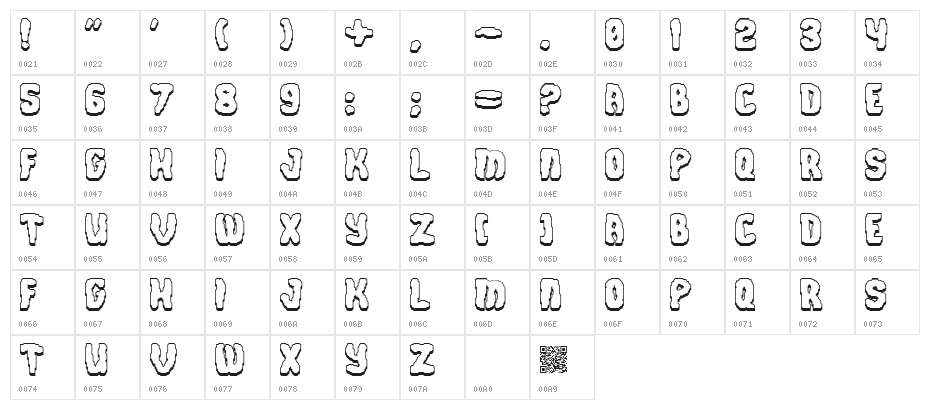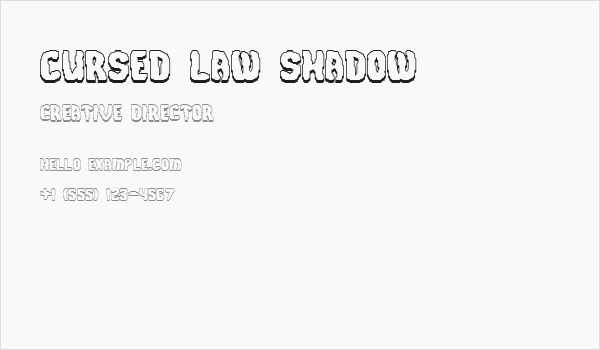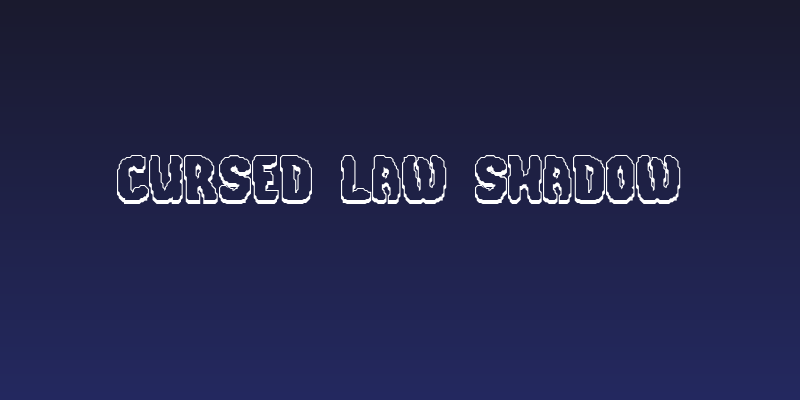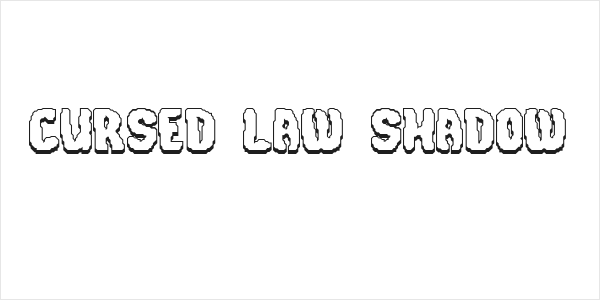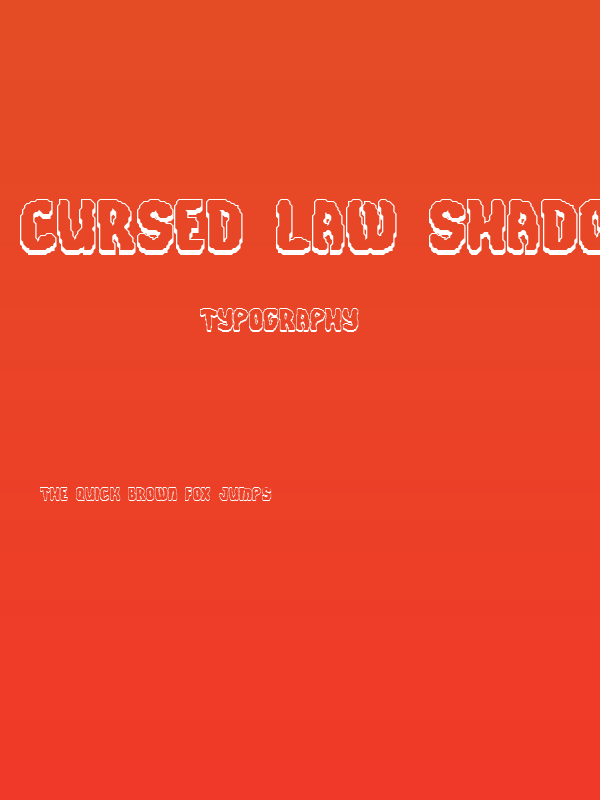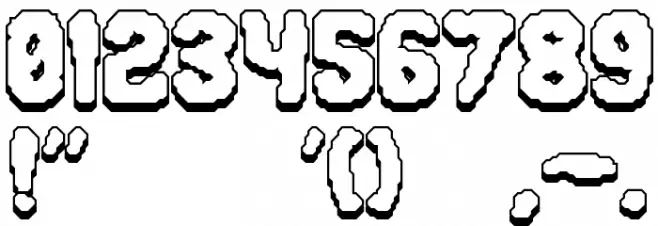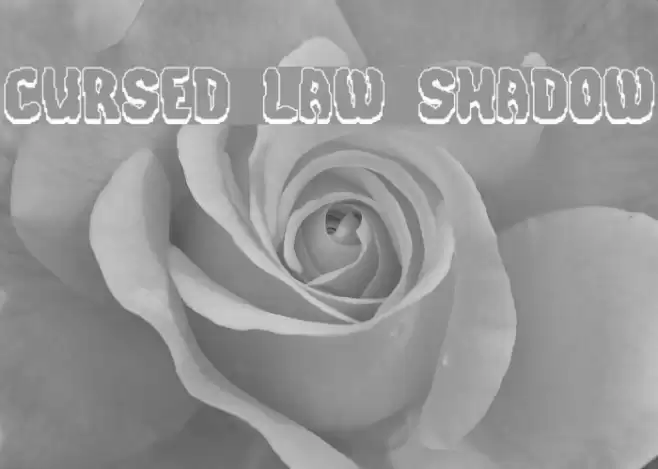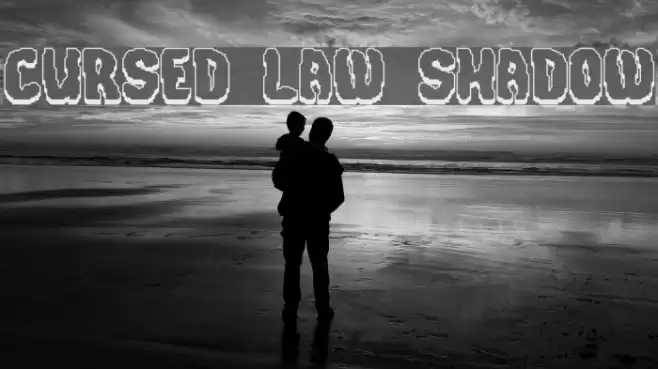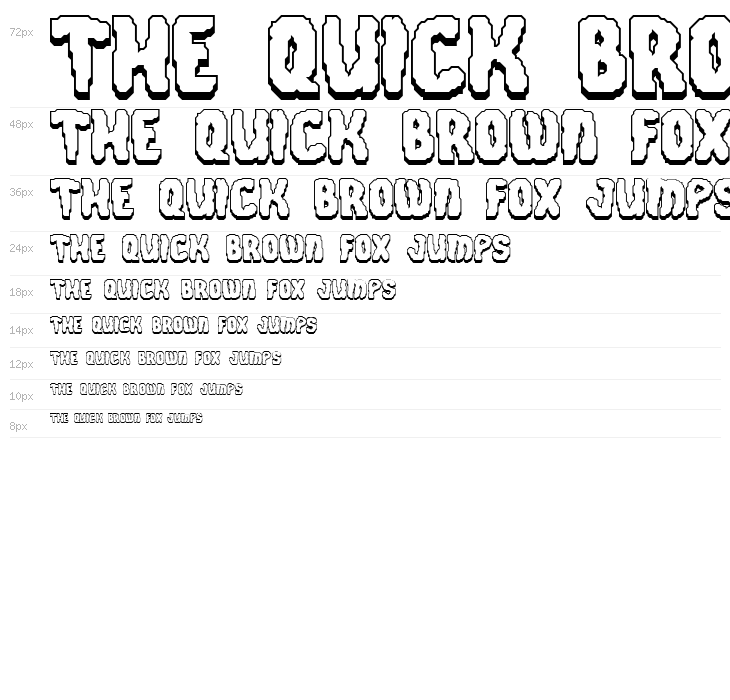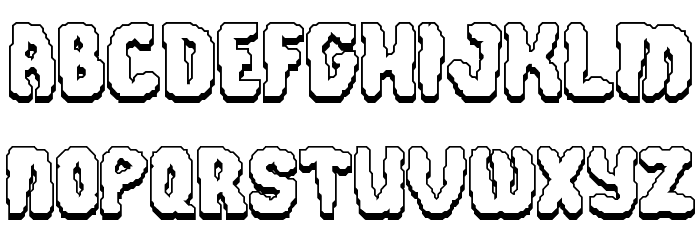
Cursed Law Shadow Font
| Estilo geral | Playful, Cartoonish, Decorative |
| Caso de uso | Headlines, Posters, Children's Books |
| Projetos propostos | Ideal for comic books, children's book covers, playful posters, and eye-catching headlines. |